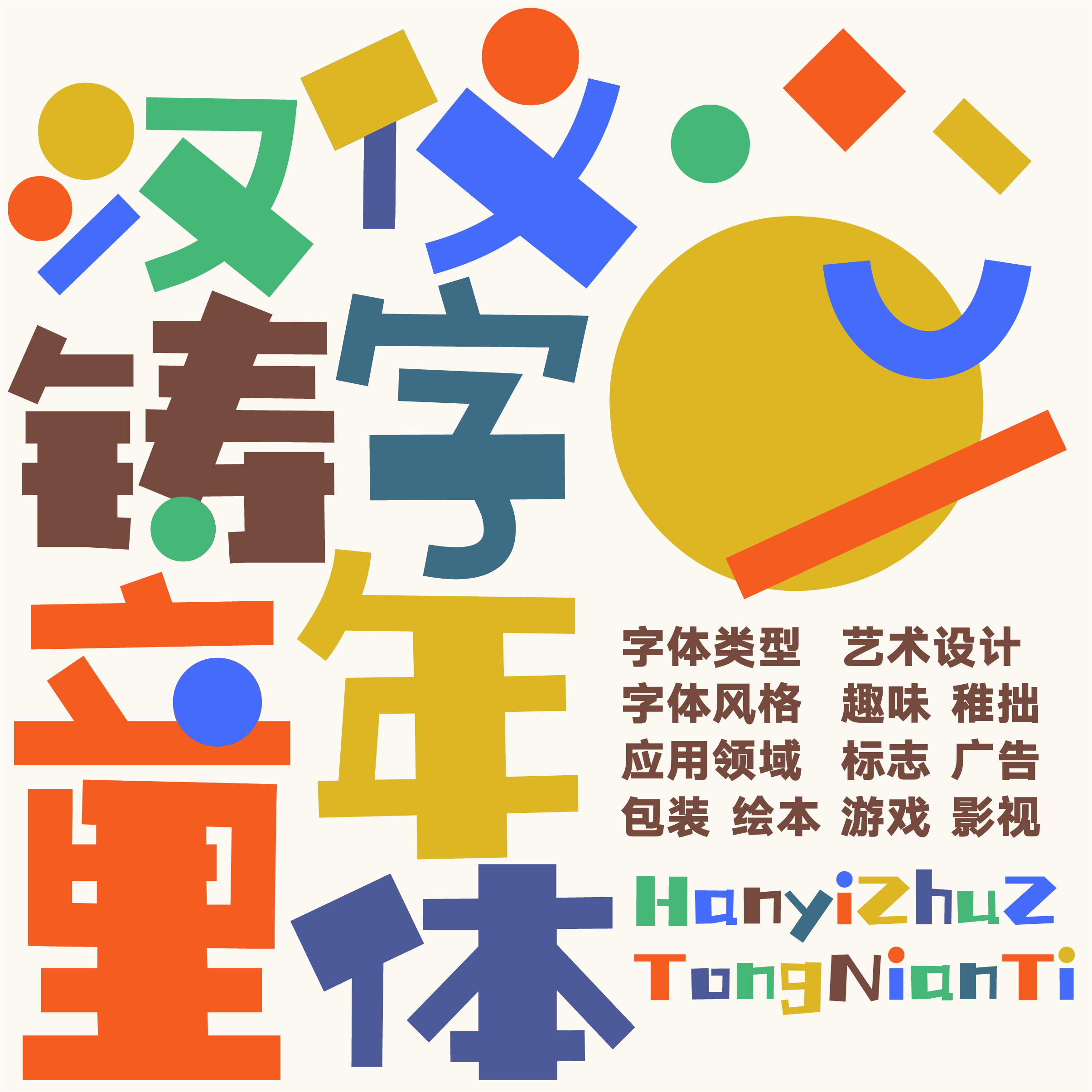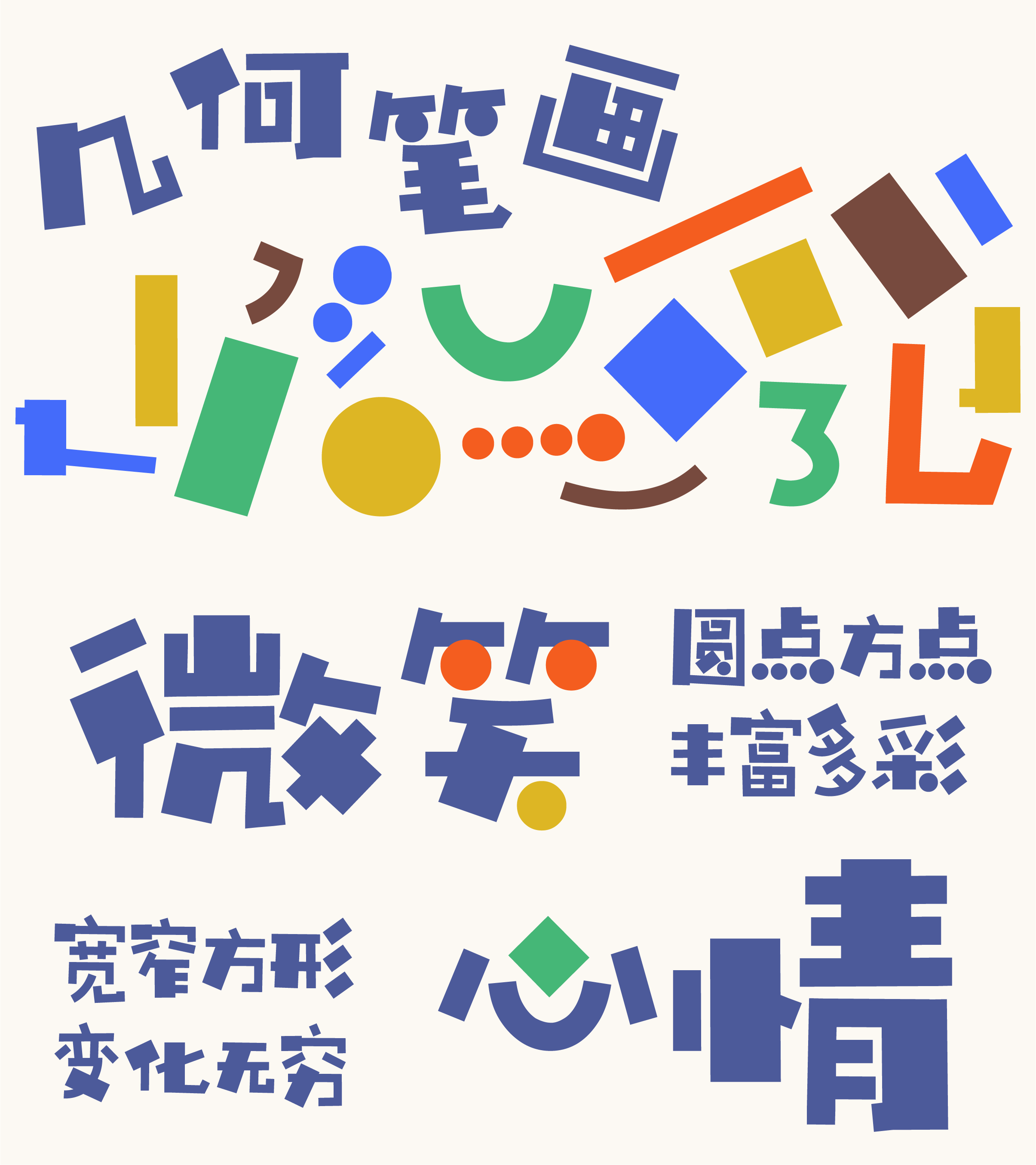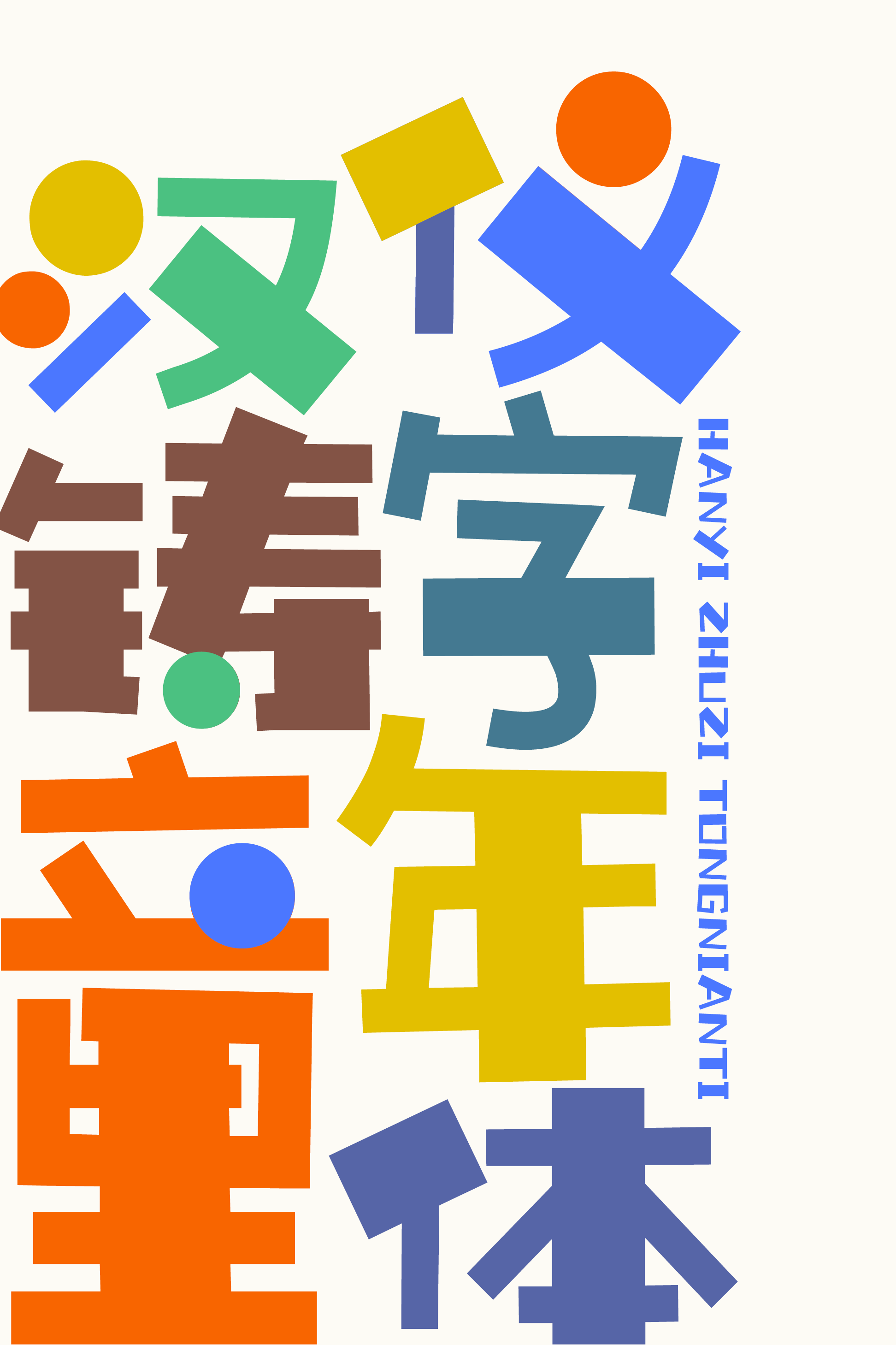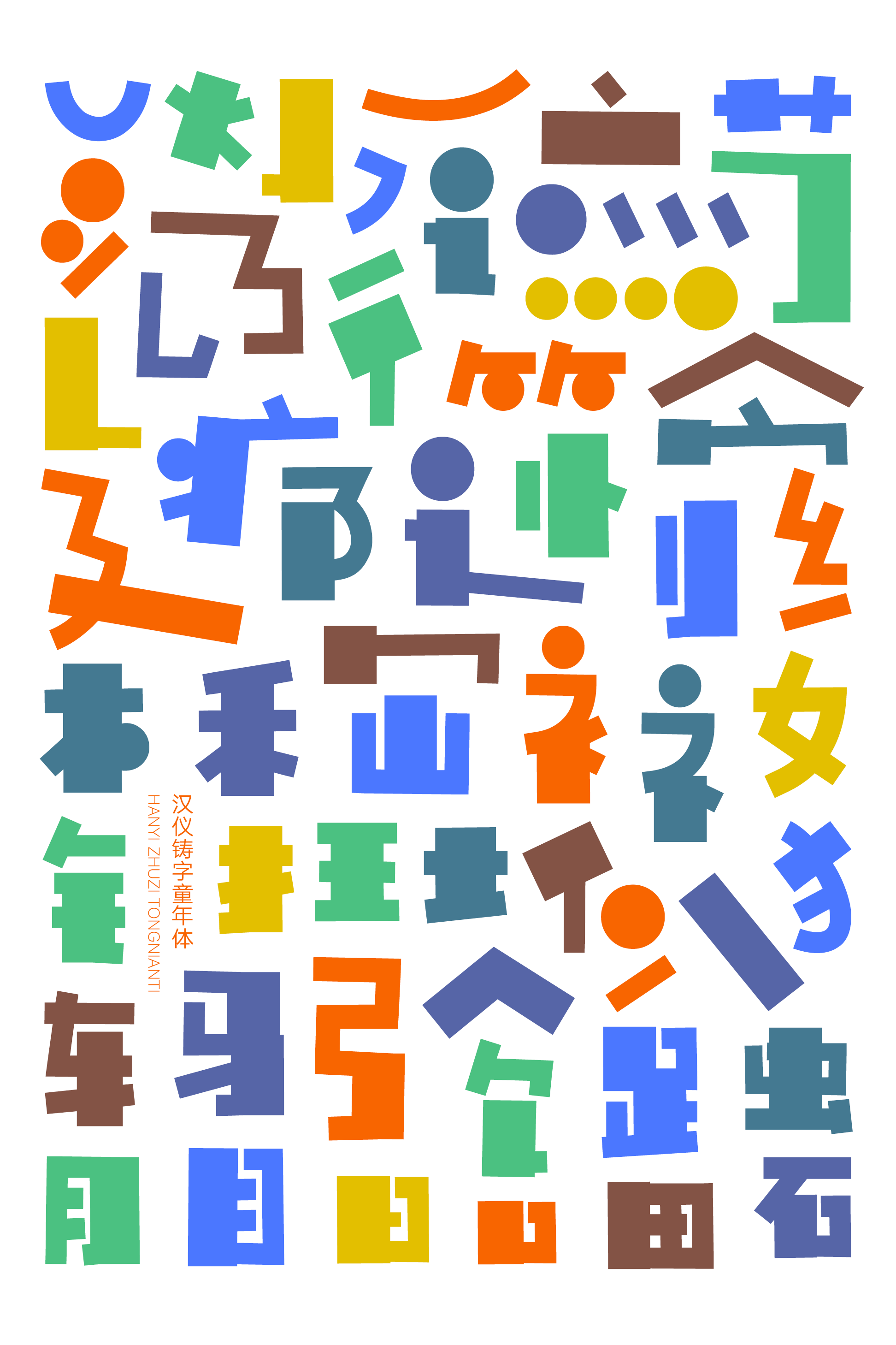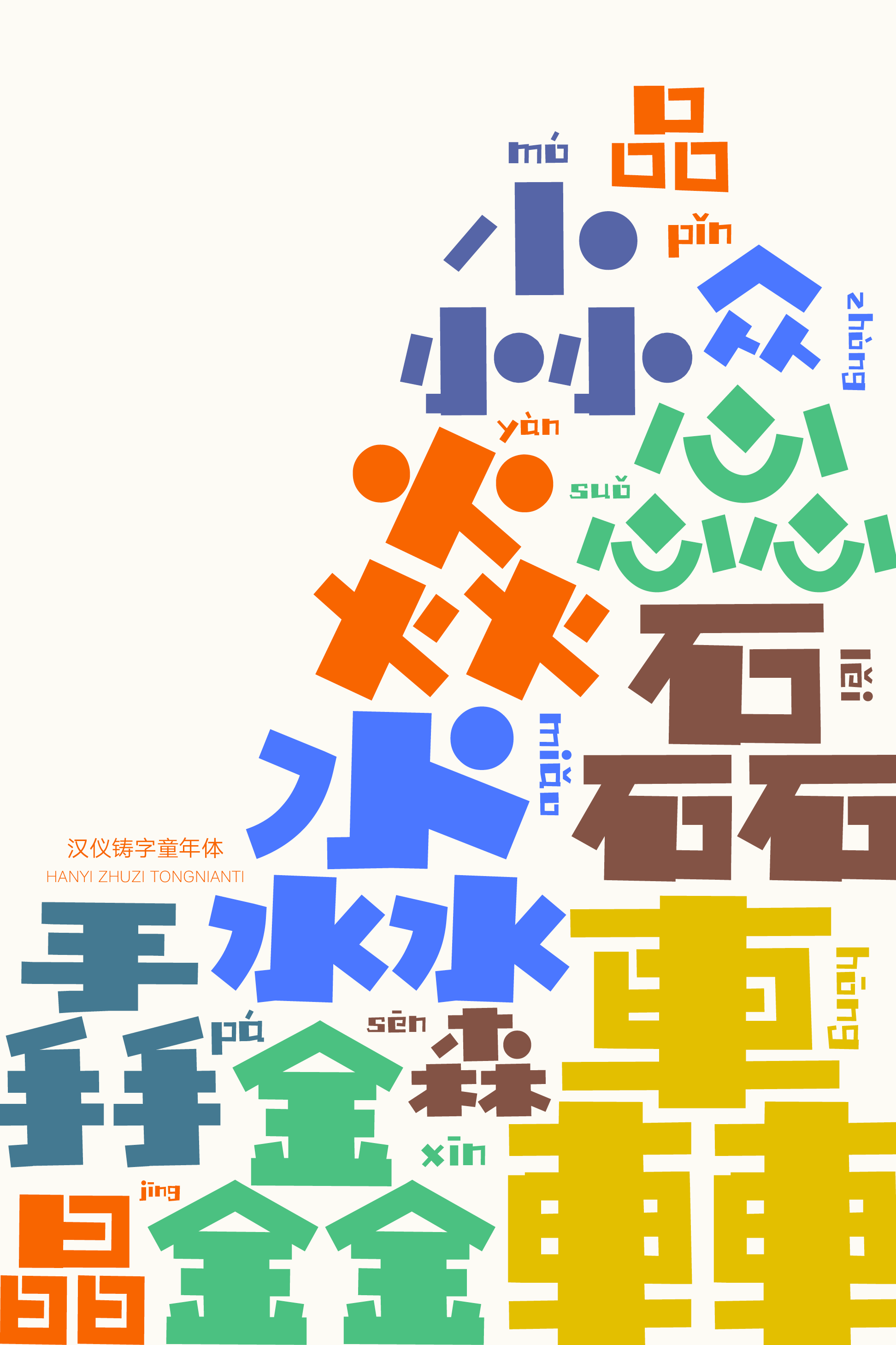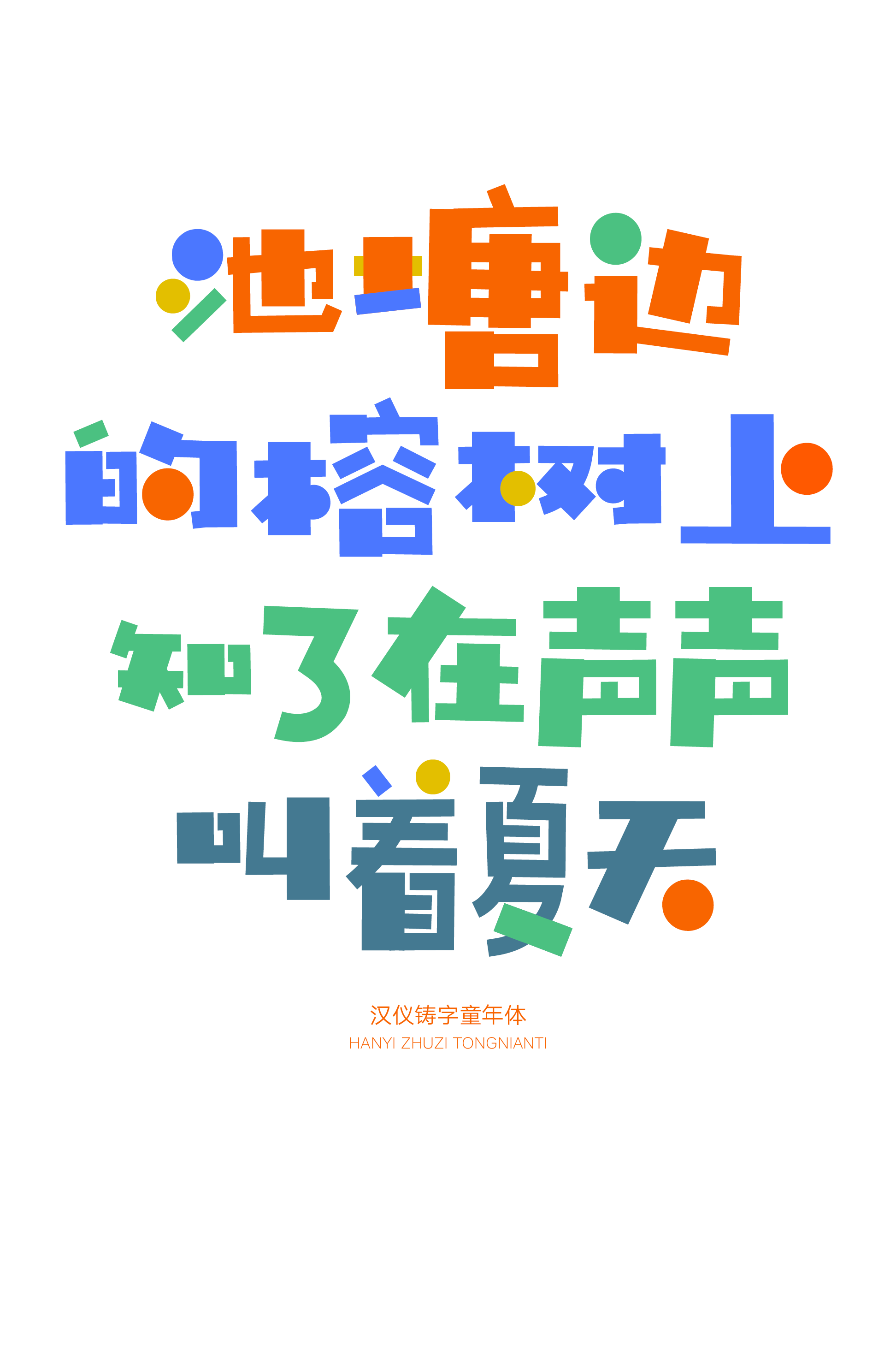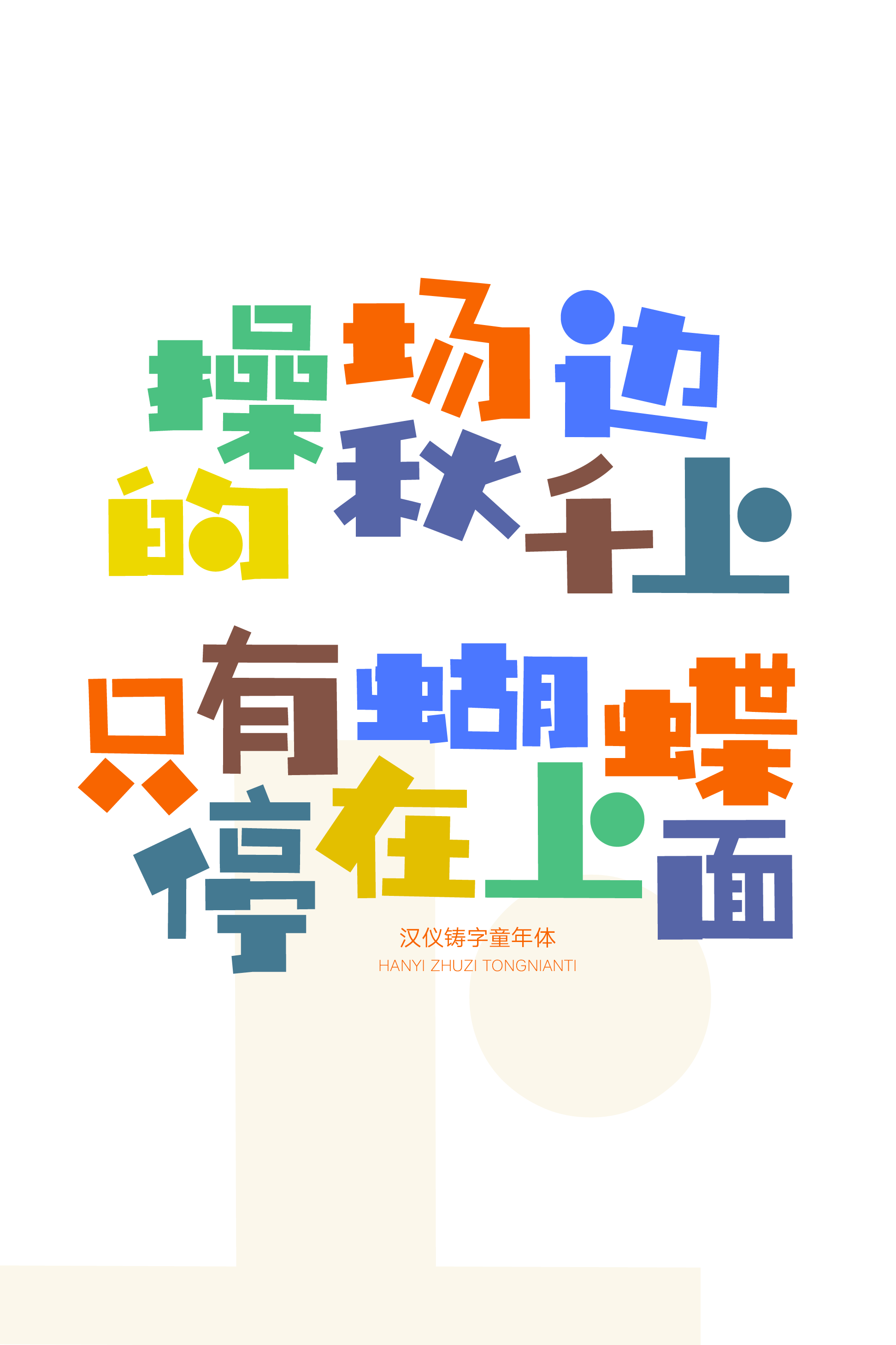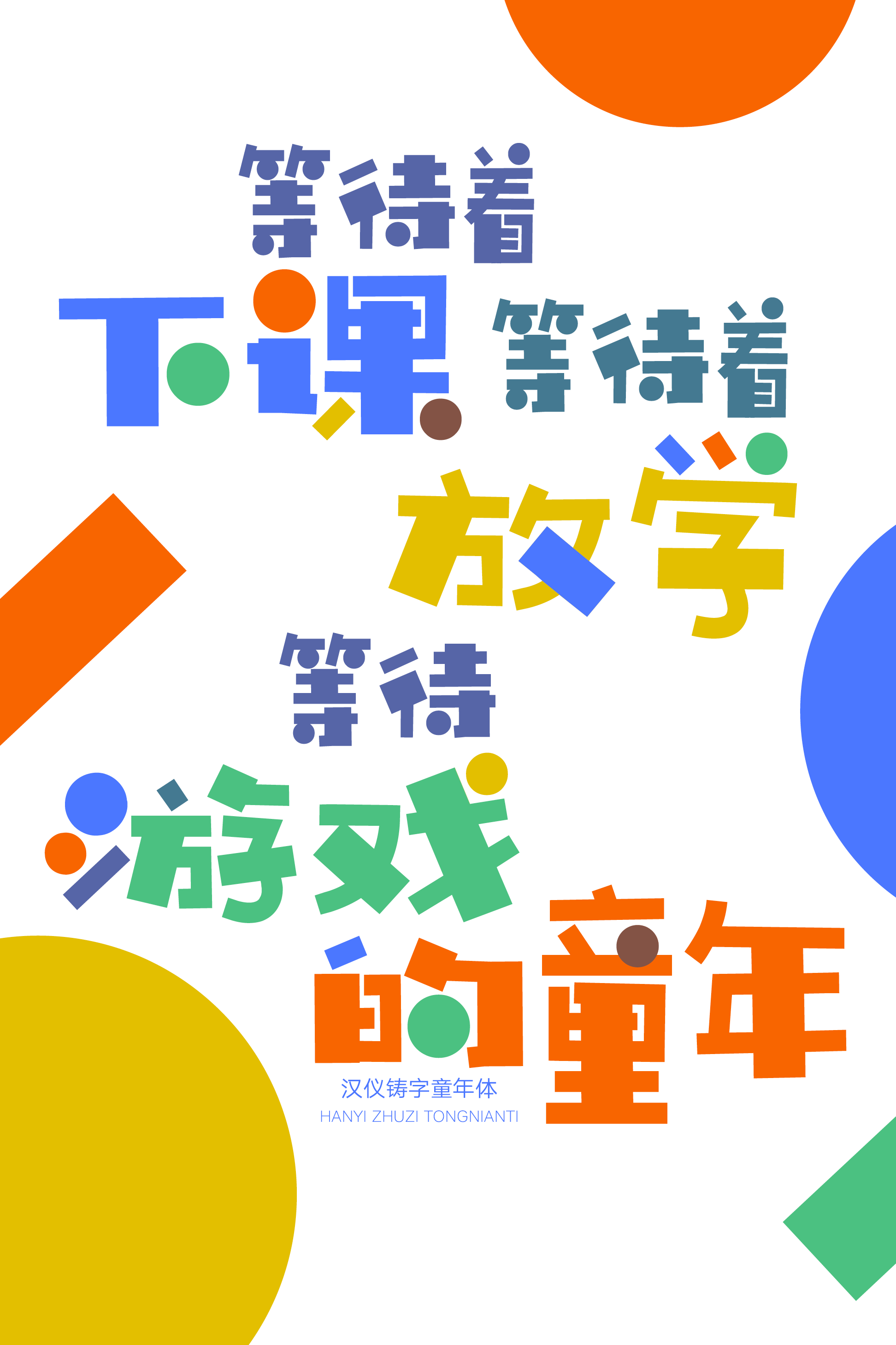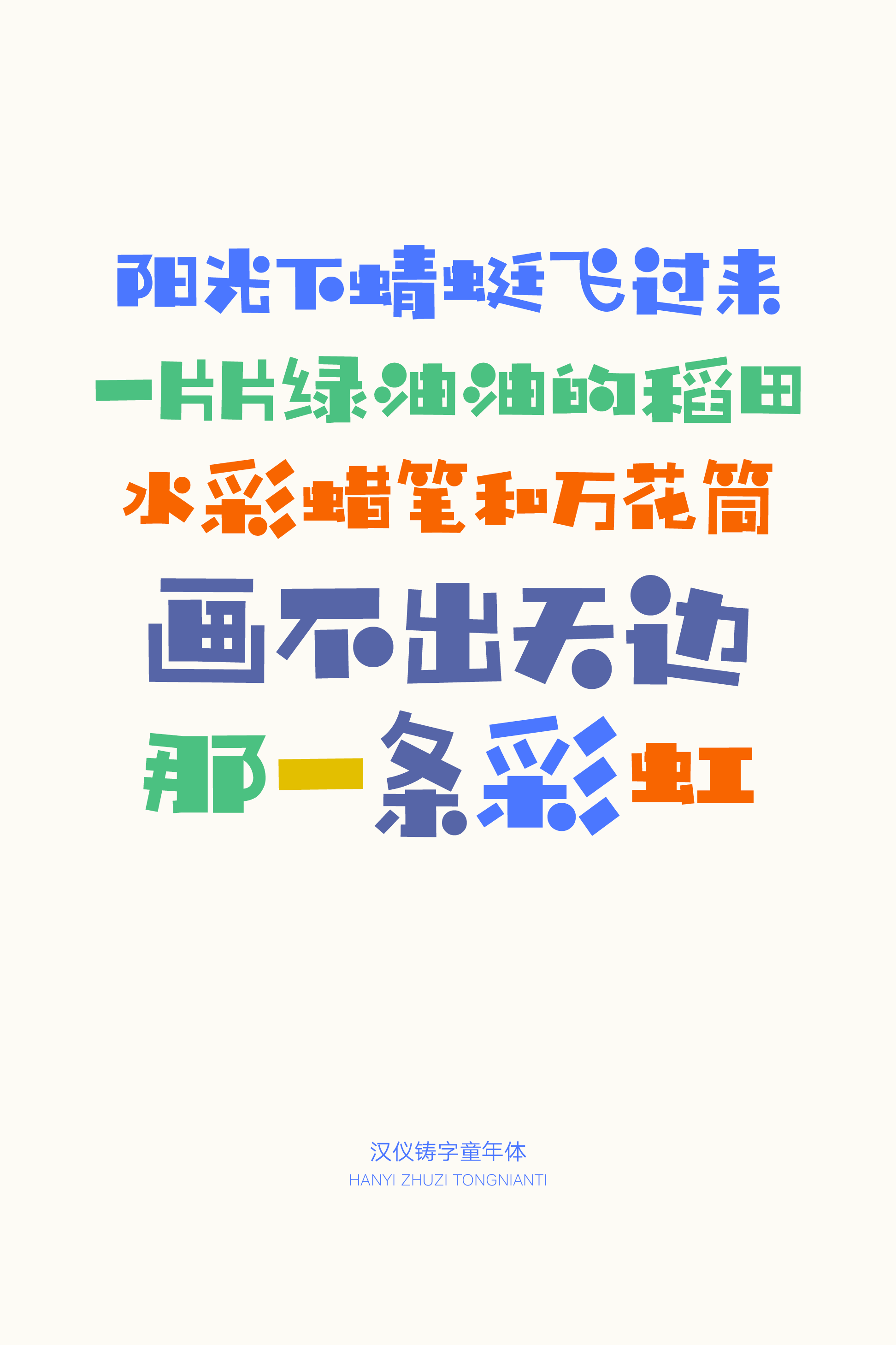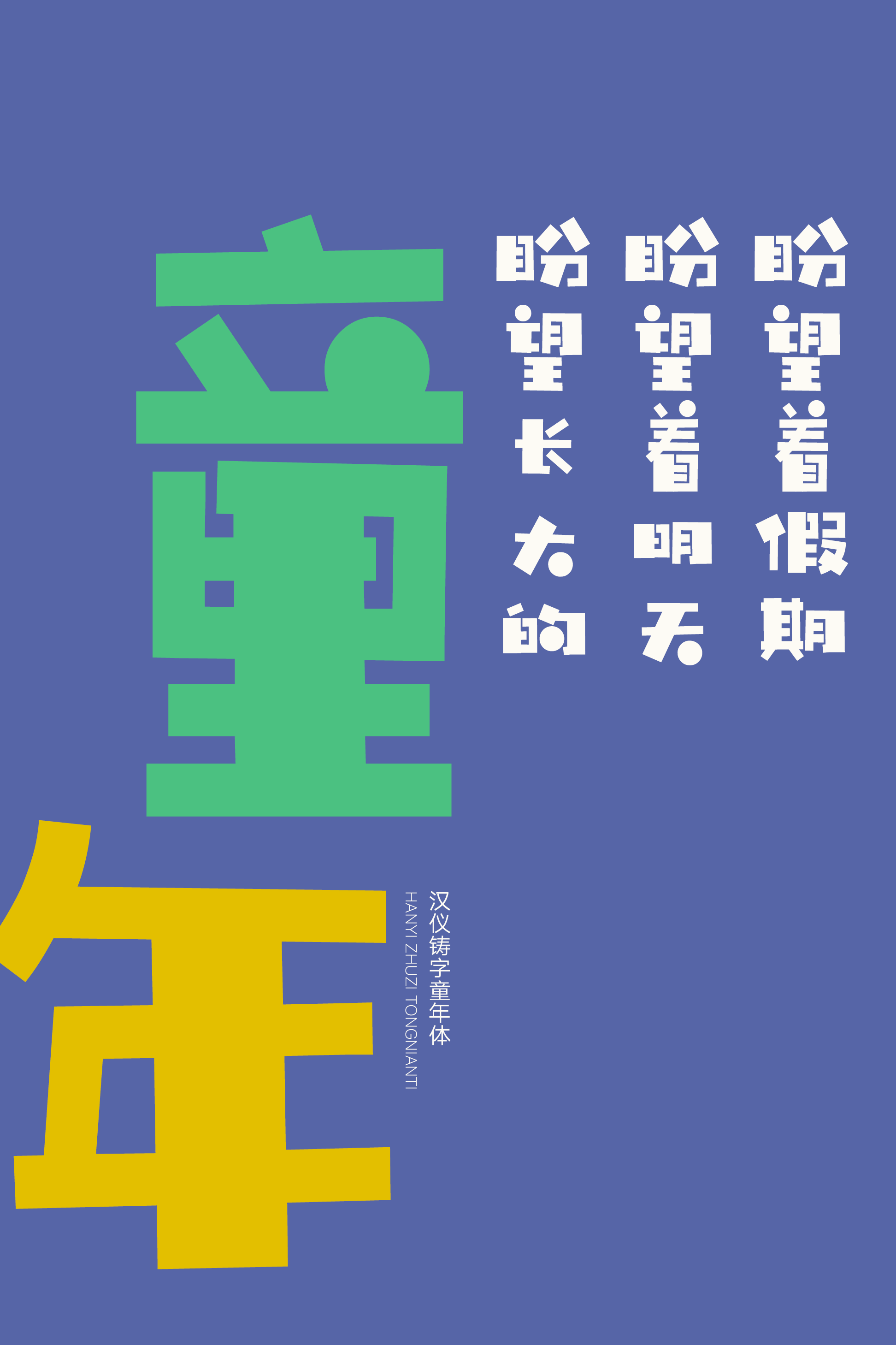
汉仪铸字童年体
童年是什么模样呢?随心所欲、蹦蹦跳跳,是充满奇思妙想的世界。由铸字社创作的汉仪铸字童年体,用几何造型的笔画构建出记忆中的童年,通过稚趣童真的字形传播无忧无虑的快乐心情。这款字体与儿童主题适配度满分,作为标题字应用于儿童节活动、游乐园设施、动画大电影等各类使用场景。
大字小字高低宽窄各有不同。
笔画由简单的几何图形构成,童趣满满。
笔形的变化充满了奇思妙想:部件在不同字形中形态各异。
汉仪铸字童年体的西文部分主要以方块造型构成,保留部分圆点,俏皮可爱。数字和符号的设计同样细节多多,充满稚趣。